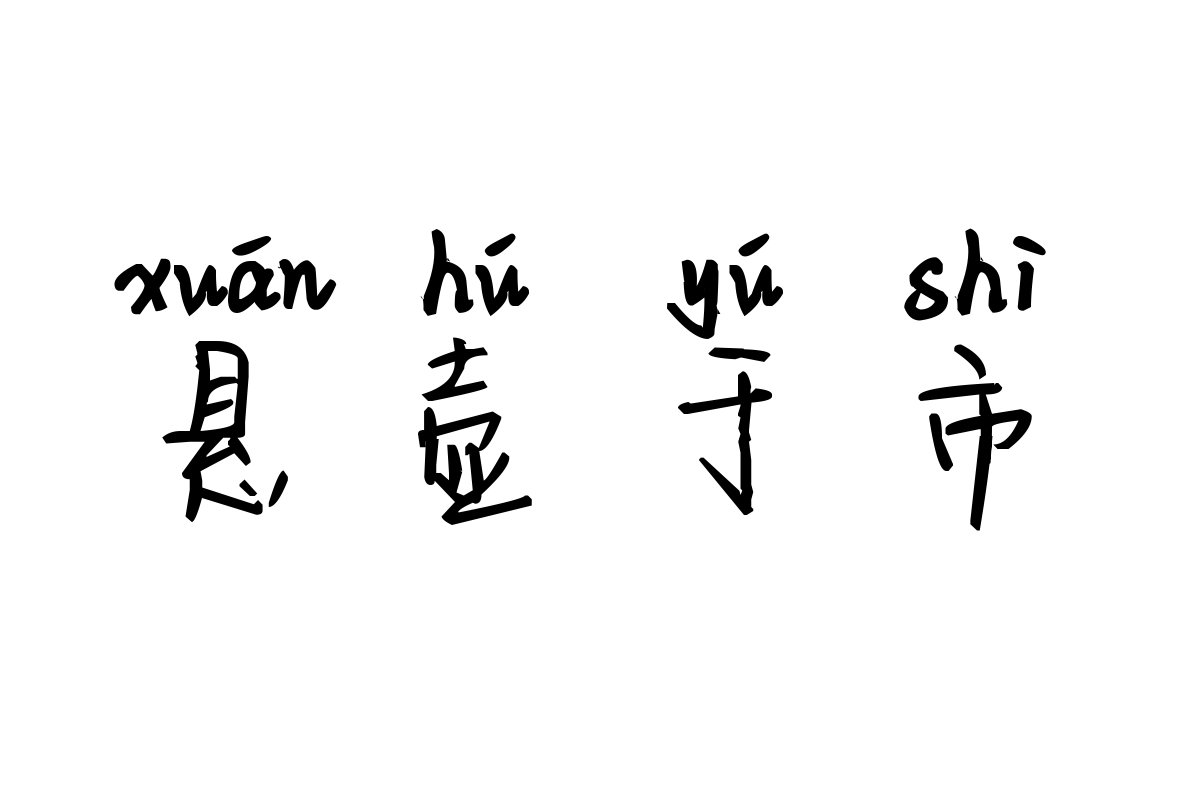
米开花样年华拼音体是一款具有中国传统美感的字体,由设计师米开设计。这款字体以优美的字形和独特的风格著称,给人一种古典而优雅的感觉。
字体特点:
1. 字形优美:米开花样年华拼音体的字形独特,线条流畅,既有传统书法的韵味,又不失现代感。
2. 笔画清晰:每个字的笔画都清晰可见,易于阅读,适合用于书写和印刷。
3. 风格独特:这款字体融合了传统书法和现代设计元素,给人一种新颖而独特的感觉。
4. 适用范围广泛:无论是用于书籍、杂志、海报还是网页设计,米开花样年华拼音体都能展现出其独特的魅力。
总体来说,米开花样年华拼音体是一款极具特色的字体,适合用于需要展示传统文化和艺术氛围的场合。